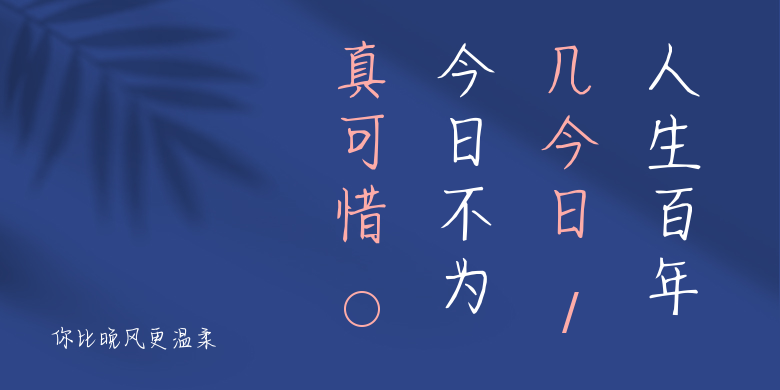
你比晚风更温柔
你比晚风更温柔,这款字体结构工整、笔画清晰,兼顾美观与易读性,适用于标题、正文、海报、包装、LOGO 等多种场景。字形优雅稳定,风格百搭耐看,适配日常排版与创意设计,让文字呈现更舒适、更具质感。你比晚风更温柔一笔一画,皆是细节,以均衡的比例、流畅的线条打造舒适视觉体验,字形端正大气,风格简约现代。无论是商业设计、品牌宣传还是日常排版,都能轻松驾驭,让文字更有格调与力量。你比晚风更温柔字体下载。